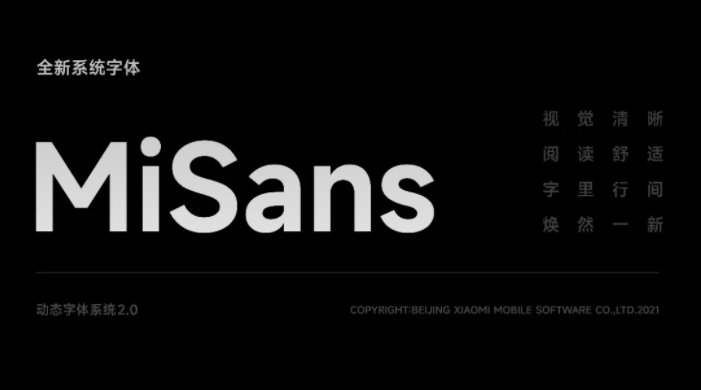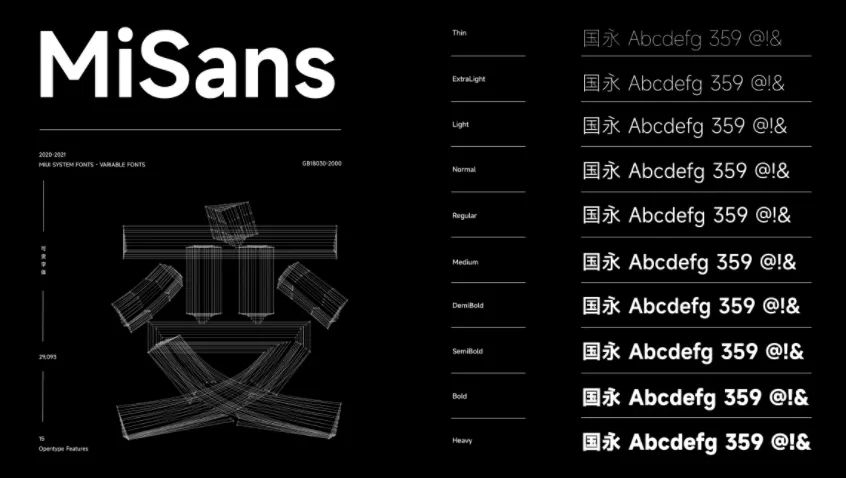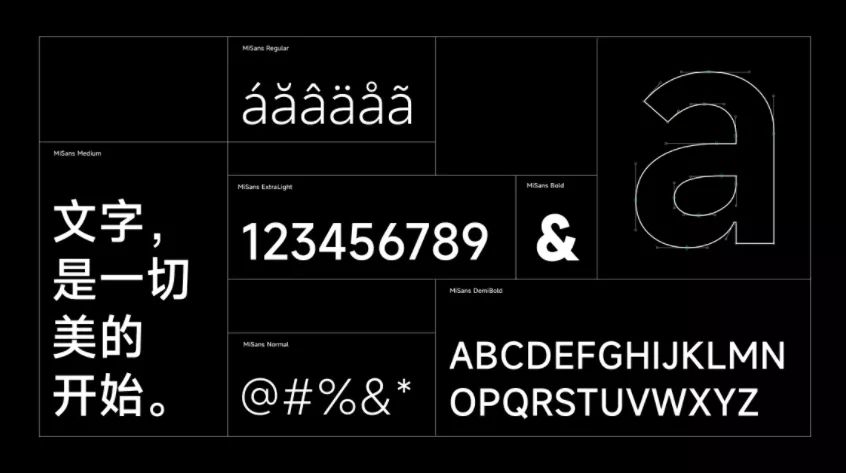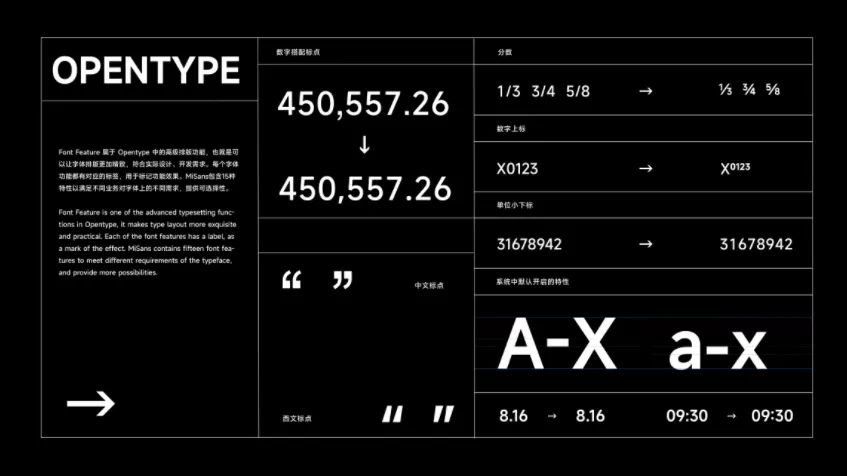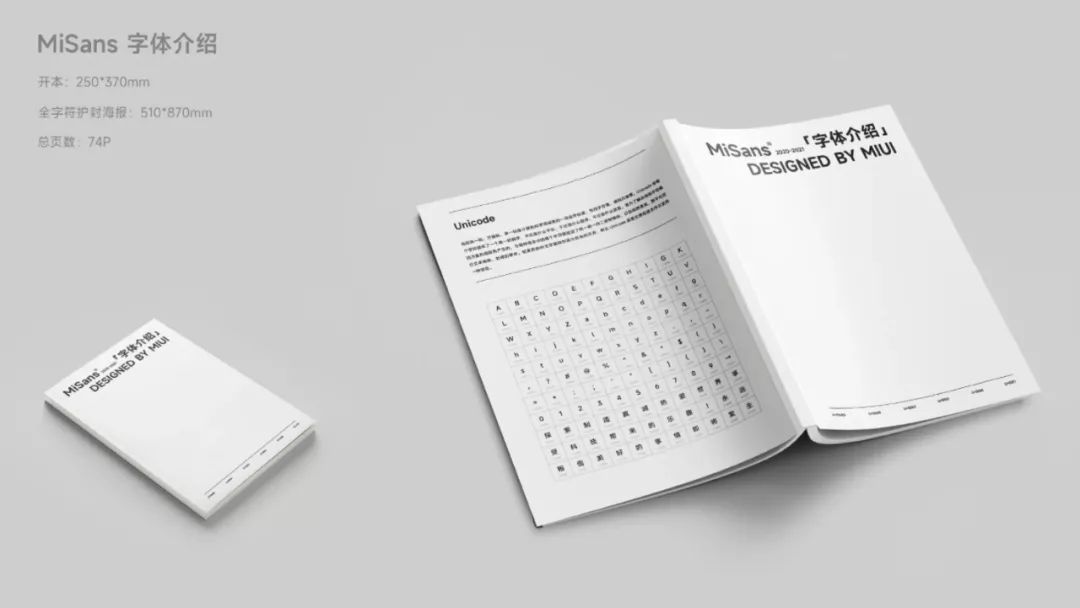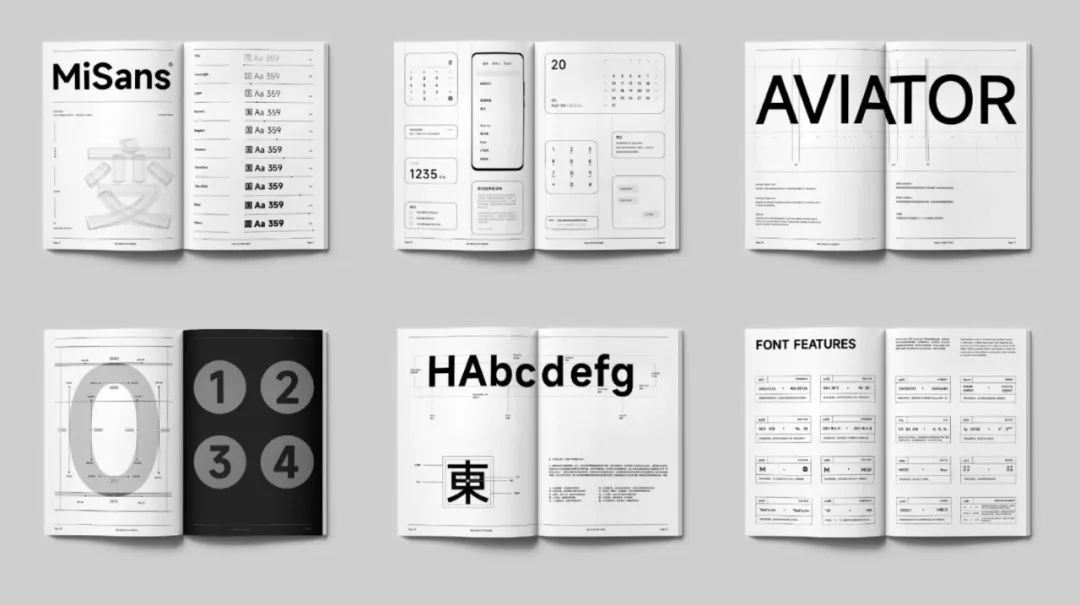
而此次的发布会中
小米还发布了一款全新的系统字体——MiSans
MIUI 13 便是采用了这种全新的系统字体
据官方介绍,
MiSans 笔型平直有力,设计更加简约,
减少视觉负担,更有利于屏幕显示。
共包含29,093个字符,支持多种语言。
其中包括10种字重,
而更重要的是
字体功能调用及实现
font-feature 属于 Opentype 中的高级排版功能,
也就是可以让字体排版更加精致,符合实际设计、开发需求,
可根据特定设计需求选择不同的字体形态。大
部分软件都可以通过 Opentype 面板访问此功能。
(部分特性在MIUI系统应用中不会默认生效)